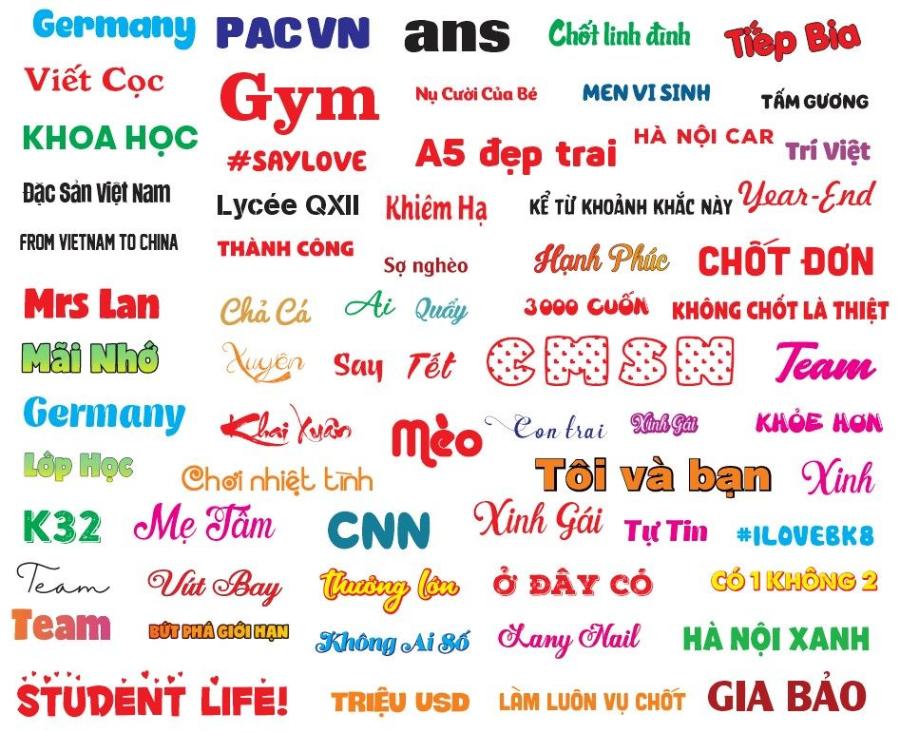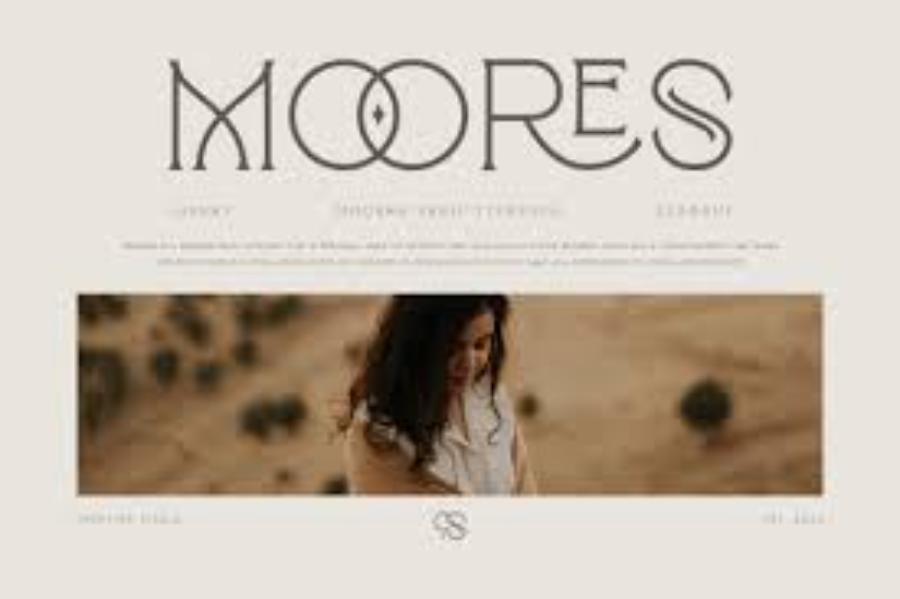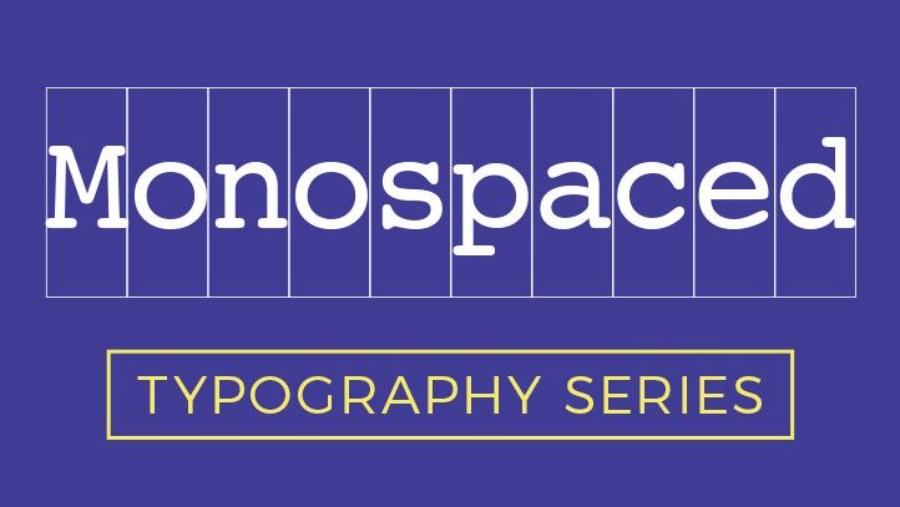
20 font chữ thiết kế đẹp phù hợp cho mọi ngành hàng năm 2025
Khám phá 20 font chữ thiết kế đẹp mắt, đa dạng phong cách, phù hợp cho mọi ngành hàng, giúp nâng tầm thương hiệu và sáng tạo trong năm 2025.
Trong thế giới thiết kế đồ họa, font chữ đóng vai trò then chốt trong việc truyền tải thông điệp, tạo dựng cá tính thương hiệu và thu hút sự chú ý của người xem. Một lựa chọn font chữ phù hợp có thể nâng tầm thiết kế, trong khi một lựa chọn sai lầm có thể phá hỏng toàn bộ nỗ lực sáng tạo. Bước sang năm 2025, xu hướng thiết kế font chữ vẫn tiếp tục phát triển, với sự kết hợp giữa nét cổ điển và hiện đại, sự tối giản tinh tế và những phá cách ấn tượng. Bài viết này sadesign sẽ giới thiệu 20 font chữ thiết kế đẹp mắt, đa dạng về phong cách và phù hợp với nhiều ngành hàng khác nhau trong năm 2025, giúp bạn có thêm những lựa chọn tuyệt vời cho các dự án sáng tạo của mình.
1. Tầm Quan Trọng Của Việc Lựa Chọn Font Chữ Phù Hợp Trong Thiết Kế
Trước khi khám phá danh sách 20 font chữ tiềm năng, hãy cùng nhau điểm qua tầm quan trọng của việc lựa chọn font chữ một cách chiến lược trong thiết kế:
• Truyền tải thông điệp và cá tính thương hiệu: Mỗi font chữ mang một "tính cách" riêng, từ trang trọng, chuyên nghiệp đến trẻ trung, năng động hay cổ điển, sang trọng. Việc lựa chọn font chữ phù hợp sẽ giúp truyền tải đúng thông điệp và cá tính mà thương hiệu muốn xây dựng.
• Tạo sự dễ đọc và trải nghiệm người dùng tốt: Một font chữ được lựa chọn tốt sẽ đảm bảo khả năng đọc dễ dàng trên mọi nền tảng và kích thước màn hình, góp phần mang lại trải nghiệm người dùng tích cực.
• Thu hút sự chú ý và tạo ấn tượng: Một font chữ độc đáo và thẩm mỹ có thể thu hút ánh nhìn và tạo ấn tượng mạnh mẽ với người xem, giúp thiết kế của bạn nổi bật giữa đám đông.
• Xây dựng sự nhất quán trong bộ nhận diện thương hiệu: Việc sử dụng một bộ font chữ nhất quán trên tất cả các ấn phẩm truyền thông sẽ giúp xây dựng sự nhận diện thương hiệu mạnh mẽ và chuyên nghiệp.
• Tăng cường hiệu quả giao tiếp: Font chữ không chỉ đơn thuần là chữ viết mà còn là một yếu tố thị giác mạnh mẽ, góp phần tăng cường hiệu quả giao tiếp và truyền tải thông tin.
2. Xu Hướng Font Chữ Thiết Kế Nổi Bật Năm 2025
Để lựa chọn được những font chữ phù hợp cho năm 2025, việc nắm bắt các xu hướng thiết kế font chữ nổi bật là rất quan trọng:
• Sự trở lại của Serif hiện đại: Các font serif với đường nét sắc sảo, tinh tế và cấu trúc hiện đại đang trở lại mạnh mẽ, mang đến cảm giác sang trọng, tin cậy và chuyên nghiệp.
• Sans-serif tối giản và linh hoạt: Các font sans-serif vẫn giữ vững vị thế nhờ tính dễ đọc và khả năng ứng dụng đa dạng trong nhiều loại hình thiết kế, đặc biệt là thiết kế web và giao diện người dùng. Xu hướng tập trung vào các biến thể hình học và tối giản.
• Font chữ viết tay (Script) tinh tế: Các font script mềm mại, uyển chuyển nhưng vẫn giữ được sự hiện đại và dễ đọc sẽ tiếp tục được ưa chuộng trong các thiết kế mang tính cá nhân, nữ tính hoặc sáng tạo.
• Font chữ hình học (Geometric Sans): Các font sans-serif dựa trên các hình học cơ bản (tròn, vuông, tam giác) mang đến cảm giác hiện đại, mạnh mẽ và cấu trúc rõ ràng.
• Font chữ monospace cách điệu: Các font monospace (mỗi ký tự có chiều rộng bằng nhau) được cách điệu với những chi tiết độc đáo sẽ tạo điểm nhấn thú vị cho các thiết kế liên quan đến công nghệ hoặc mang phong cách retro.
• Font chữ biến thể (Variable Fonts): Cho phép điều chỉnh nhiều thuộc tính của font chữ (độ dày, độ rộng, độ nghiêng...) trong một file duy nhất, mang lại sự linh hoạt cao trong thiết kế.
3. 20 Font Chữ Thiết Kế Đẹp Cho Các Ngành Hàng Năm 2025
Dưới đây là 20 font chữ thiết kế đẹp mắt, được lựa chọn dựa trên xu hướng và khả năng ứng dụng trong nhiều ngành hàng khác nhau trong năm 2025:
3.1. Serif Hiện Đại (Modern Serif)
1. Recoleta: Một font serif quyến rũ với các đường cong mềm mại và nét chữ hiện đại, phù hợp cho ngành thời trang, mỹ phẩm, nhà hàng cao cấp.
2. Playfair Display: Một font serif thanh lịch và trang trọng với các nét dày mỏng tương phản rõ rệt, lý tưởng cho tiêu đề, logo và các thiết kế mang tính nghệ thuật.
3. Bodoni Moda: Phiên bản hiện đại của font Bodoni cổ điển, mang đến vẻ đẹp sang trọng, tinh tế và phù hợp cho ngành thời trang, tạp chí cao cấp.
4. Cormorant Garamond: Một font serif cổ điển được làm mới với các đường nét thanh mảnh và duyên dáng, thích hợp cho ngành văn học, nghệ thuật, giáo dục.
3.2. Sans-serif Tối Giản và Linh Hoạt (Minimalist & Versatile Sans-serif)
1. Inter: Một font sans-serif được thiết kế đặc biệt cho giao diện người dùng, với khả năng đọc tuyệt vời trên mọi kích thước màn hình. Phù hợp cho công nghệ, website, ứng dụng.
2. Poppins: Một font sans-serif hình học với nhiều biến thể độ dày, mang đến sự hiện đại, trẻ trung và dễ dàng sử dụng trong nhiều loại hình thiết kế.
3. Montserrat: Lấy cảm hứng từ bảng hiệu cổ điển ở Buenos Aires, Montserrat mang đến vẻ đẹp hình học mạnh mẽ và hiện đại, phù hợp cho logo, tiêu đề và văn bản.
4. Nunito Sans: Một font sans-serif mềm mại và tròn trịa, tạo cảm giác thân thiện, gần gũi và phù hợp cho ngành thực phẩm, trẻ em, giáo dục.